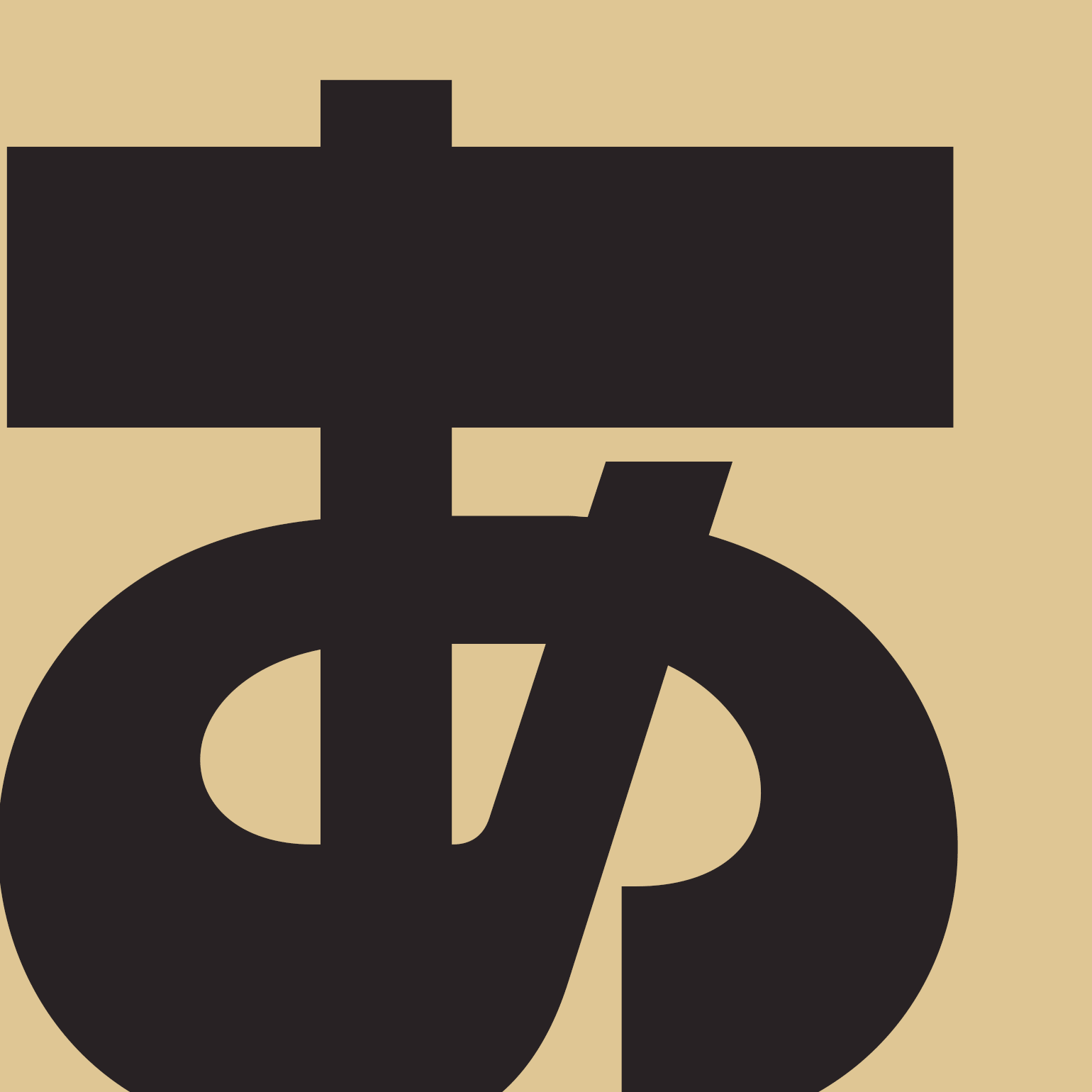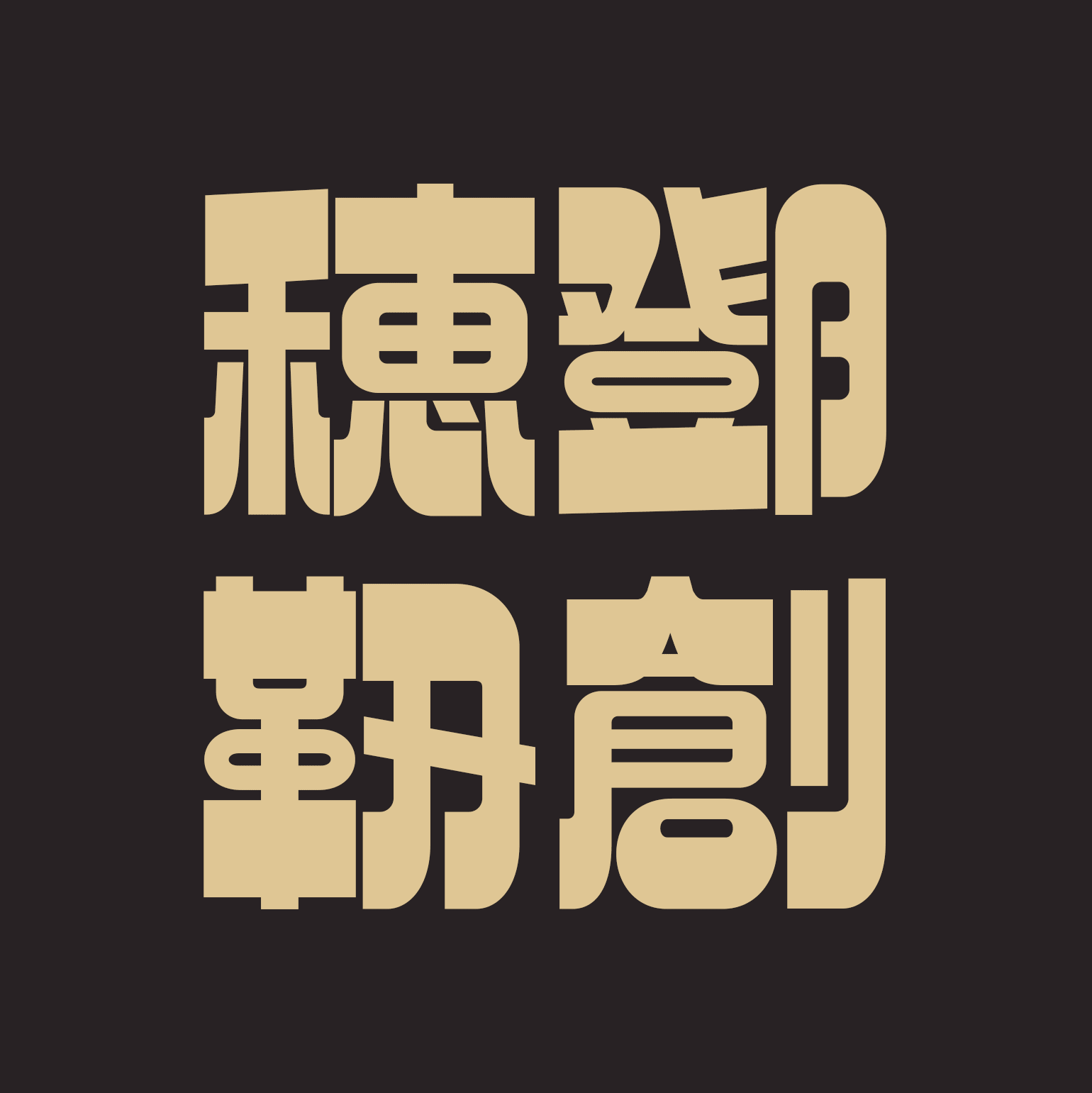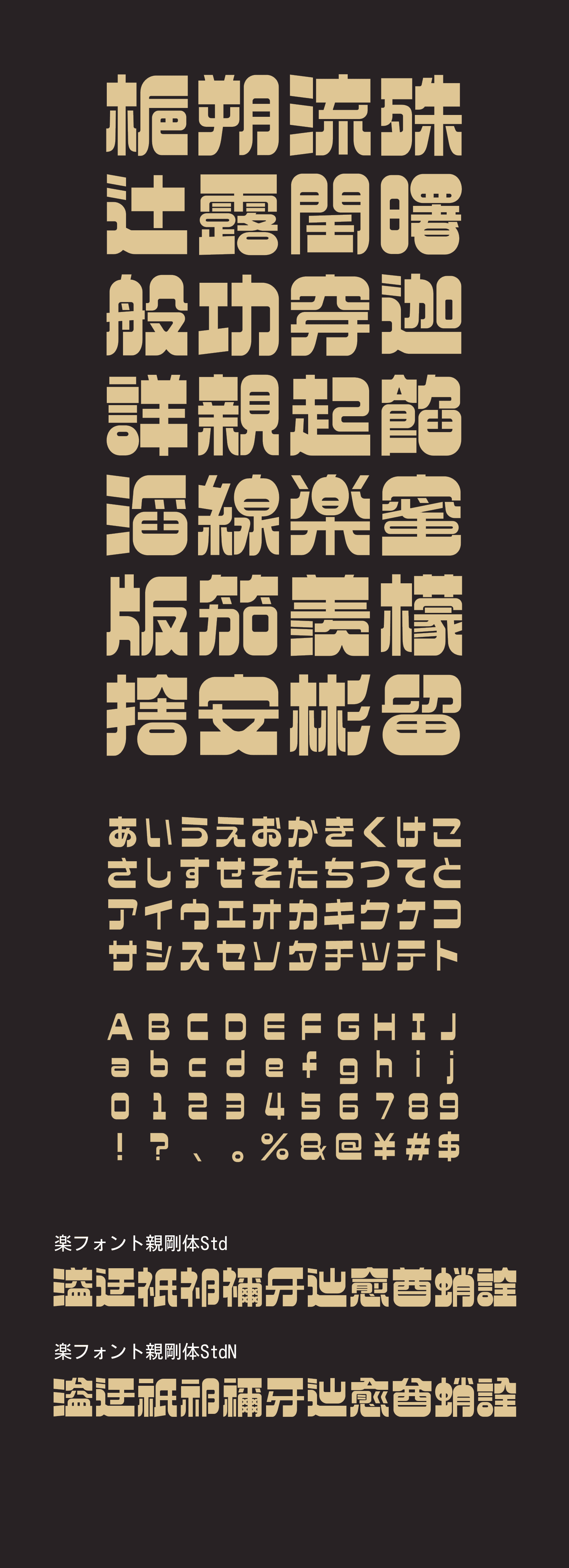
親剛体(しんごうたい)
縦画と横画の線幅のコントラストによって生み出される圧倒的インパクトと、滑らかでやわらかいカーブの組み合わせが特徴的な書体です。 密度の高い大胆なデザインながら、カッティングに几帳面な正方形を意識することにより、重量感に負けない可読性を保っています。 線幅のスタイルは文字ごとに自由に設計されており、どっしりとした文字組みの中にも、どこかリズミカルな印象を。 その名の通り、「親しみやすく」「つよい」。 オープンでインパクトあるイメージを求めるロゴや見出しに最適です。